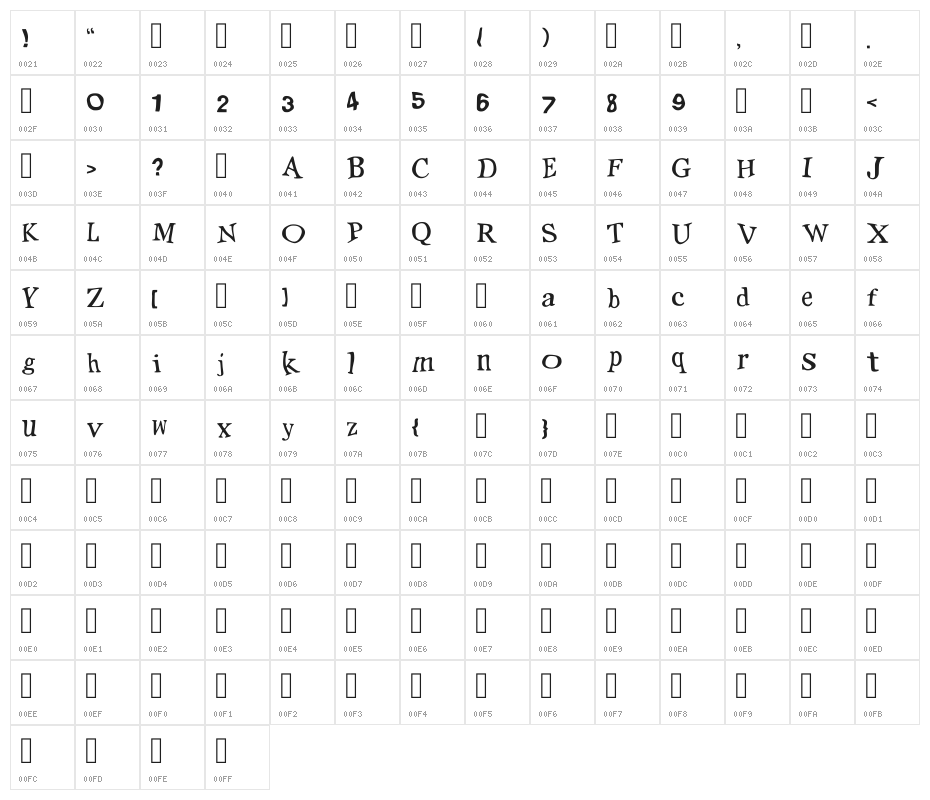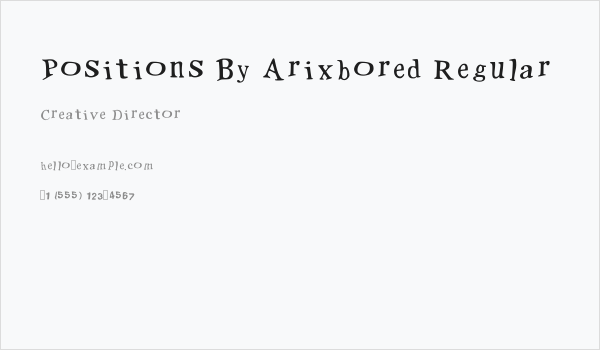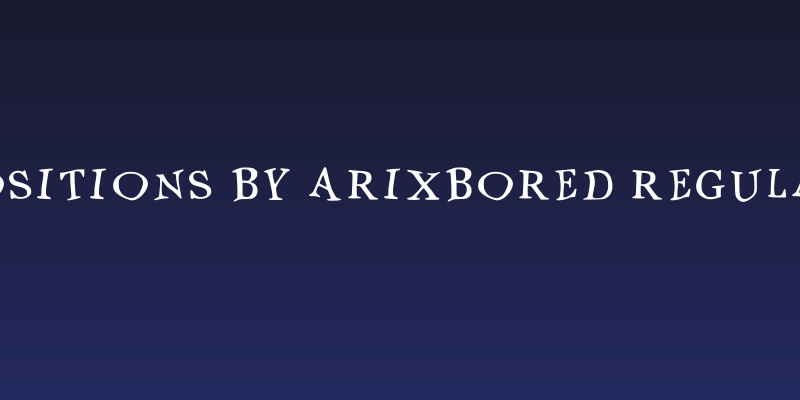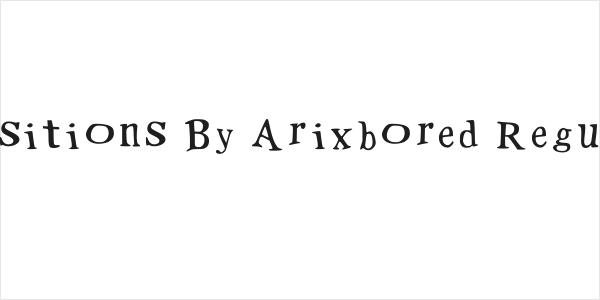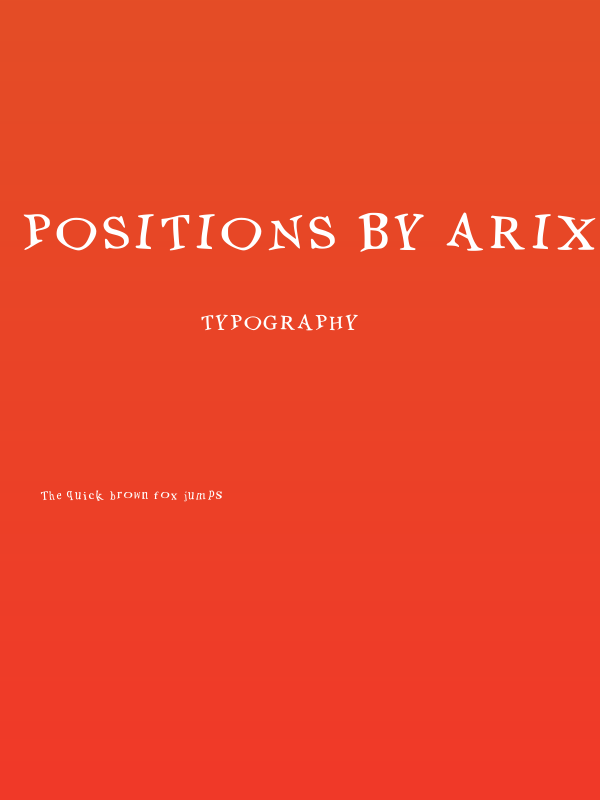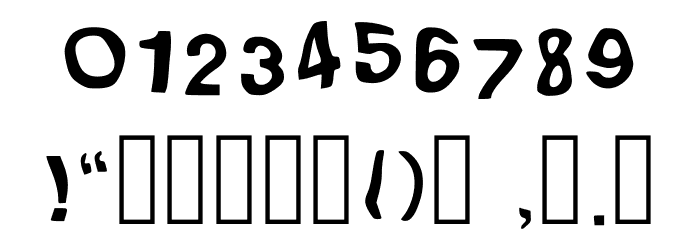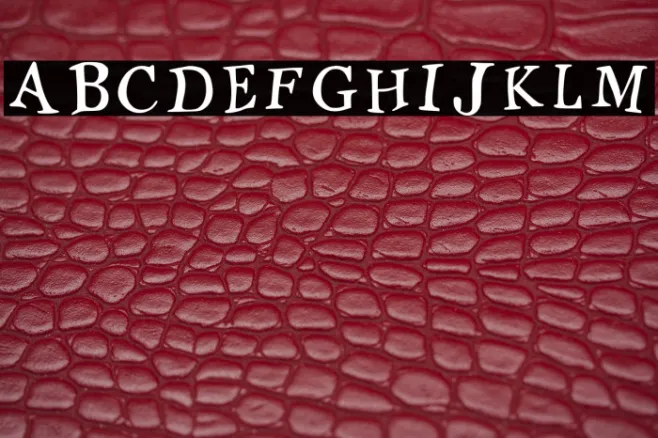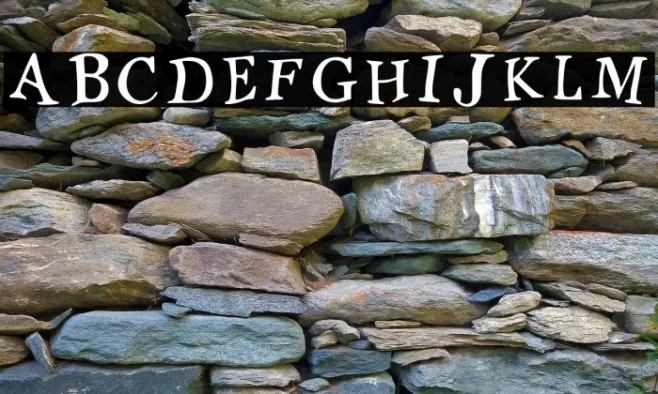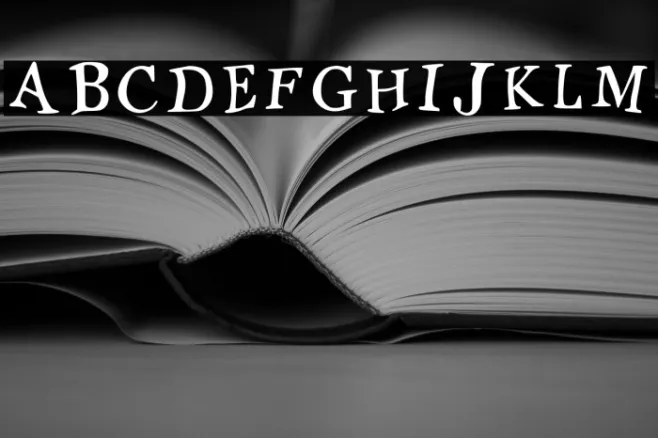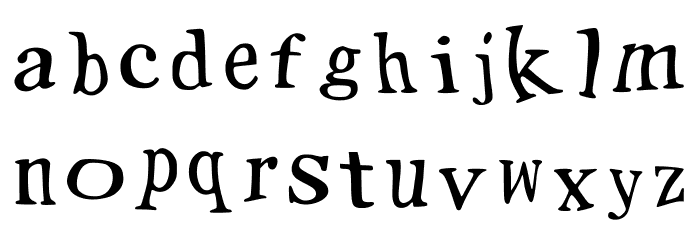
Positions By Arixbored Regular Font
| Anwendungsfall | Logos, Posters, Creative projects |
| Vorgeschlagene Projekte | Ideal for children's books, creative posters, and artistic branding projects. |